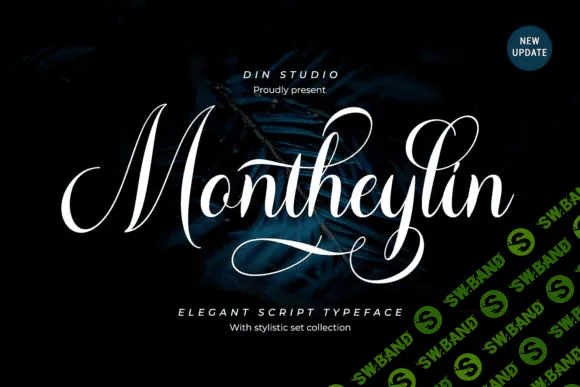
Монтейлин чувствует себя невероятно элегантно и плавно.
Он выглядит потрясающе на свадебные приглашения, благодарственные открытки, цитаты, поздравительные открытки, логотипы, визитные карточки и любой другой дизайн, который нуждается в рукописном прикосновении.
Он имеет различные базовые, плавные линии, великолепные глифы и потрясающие альтернативы.